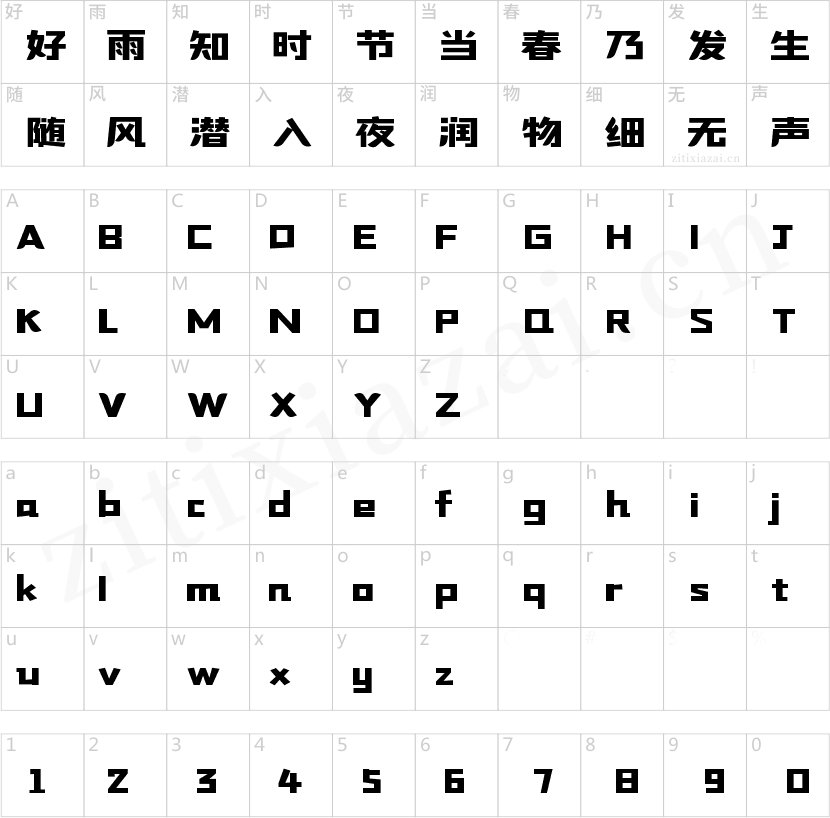
壹心粉笔头
壹心粉笔头,这款字体结构工整、笔画清晰,兼顾美观与易读性,适用于标题、正文、海报、包装、LOGO 等多种场景。字形优雅稳定,风格百搭耐看,适配日常排版与创意设计,让文字呈现更舒适、更具质感。壹心粉笔头一笔一画,皆是细节,以均衡的比例、流畅的线条打造舒适视觉体验,字形端正大气,风格简约现代。无论是商业设计、品牌宣传还是日常排版,都能轻松驾驭,让文字更有格调与力量。壹心粉笔头字体下载。